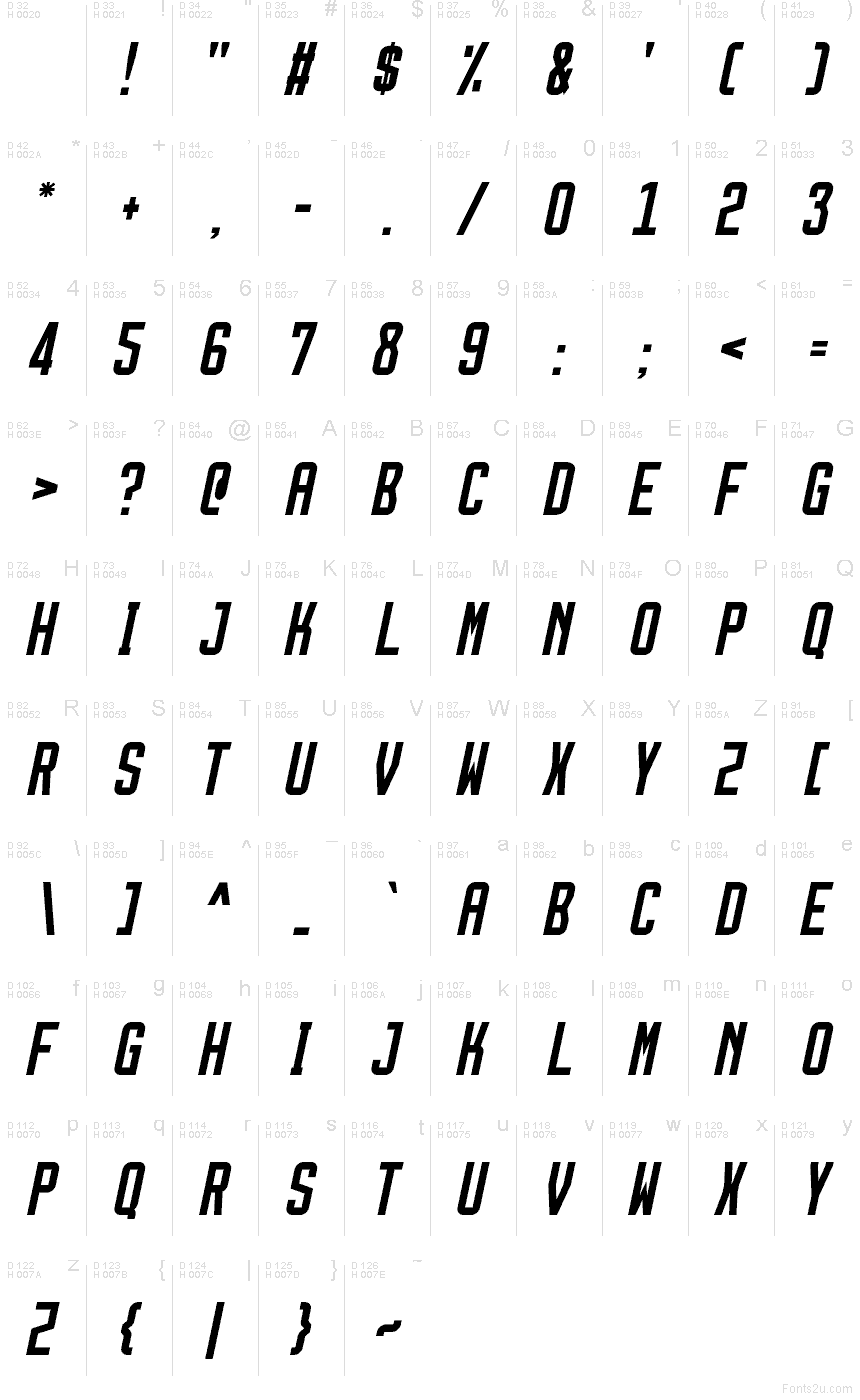
Thernaly Italic
Thernaly Italic, créée par GGBotNet, est une police sans empattement italique gratuite, caractérisée par des formes de lettres inclinées, serrées et des découpes angulaires nettes. Le design dégage une impression de compression et de mouvement vers l'avant, avec des proportions étroites et des traits droits qui confèrent une rythmique graphique élancée.
Thernaly Italic est idéale pour les titres d'affiches, les graphismes sportifs, les pochettes d'albums, les logos et la signalétique courte, car sa structure oblique apporte une énergie sans surcharge décorative. Cette police gratuite confère une dynamique directionnelle claire aux projets d'image de marque et aux mises en page d'affichage nécessitant une ligne de texte forte et compacte.